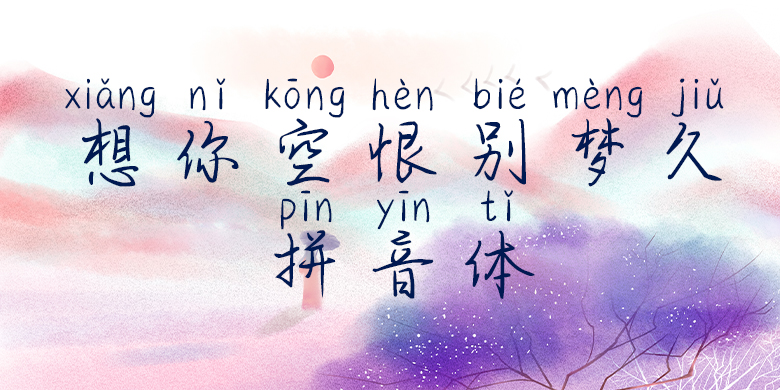
方正手迹-想你空恨别梦久拼音体
方正手迹-想你空恨别梦久拼音体,这款字体结构工整、笔画清晰,兼顾美观与易读性,适用于标题、正文、海报、包装、LOGO 等多种场景。字形优雅稳定,风格百搭耐看,适配日常排版与创意设计,让文字呈现更舒适、更具质感。方正手迹-想你空恨别梦久拼音体一笔一画,皆是细节,以均衡的比例、流畅的线条打造舒适视觉体验,字形端正大气,风格简约现代。无论是商业设计、品牌宣传还是日常排版,都能轻松驾驭,让文字更有格调与力量。方正手迹-想你空恨别梦久拼音体字体下载。
想你空恨别梦久拼音体是一款行书为底添加拼音的手写体。该字体笔画粗细变化,连笔流畅,松紧适中有一种韵律感。该字体适用于文艺类的书刊、品牌广告和产品包装设计,以及社交网络的个性化用字。